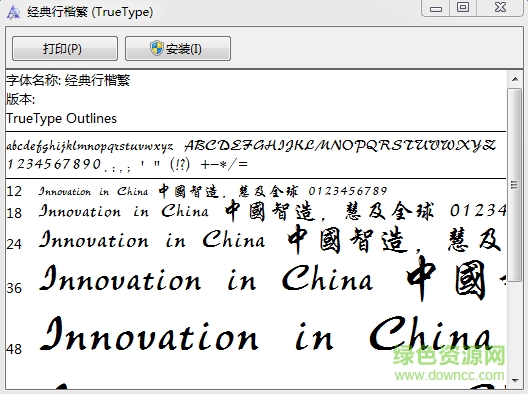
軟件介紹 軟件標簽: 經典字體 字體 經典行楷繁字體是經典字庫里的一款繁體字體,這款字體寫出來的字是俊秀美觀的,有著它獨特的特色與魅力,也是很多人都喜歡的一款字體,大家如果有需要的話可以來綠色資源網下載。安裝說明:方法一:控制面板/字體/文件/安裝新字體;方法二:直接將字體復制到C:\WINDOWS\Fonts。方法三:針對win7系統(tǒng),用戶只需選中字體右鍵安裝即可。注意事項本站所有字體資源僅供個人學習與參考,如需商業(yè)使用請到相關官網授權。 軟件截圖 上一張下一張(1 / 1) 安裝詳細截圖 猜你喜歡 行楷字體 經典字體 行楷字體 行楷字體大全是綠色資源網小編為大家打包整理的行楷字體ttf合集,包含了幾十款應用極廣的行楷體,適用于影視、廣告、平面、印刷各種行業(yè)領域,選擇多樣,下載便捷! 查看更多>> 漢儀蘇澤立行楷精修版簡 3.01M/中文/4.0/免費版下載 漢儀許靜行楷字體 2.44M/中文/4.4/下載 繁體行楷字體大全 46.87M/中文/2.5/下載 經典行楷簡體 常規(guī) 5.54M/中文/2.3/下載 文星簡行楷 3.41M/中文/6.6/下載 stxingkai 3.41M/中文/6.3/免費版下載 經典字體 綠色資源網小編為大家收集了經典字體的各種書體,比如經典綜藝體簡體,這種經典字體的整個字體效果還具有卡通元素;經典黑體簡是一款典型的簡體字體,是現(xiàn)代中文的一種標準化寫法,與繁體中文(又稱正體中文)相對等等,還有經典細宋簡、經典毛筆字體、經典繁淡古...,這一類字體在廣告設計、平面設計、學習等都有廣泛的應用,一次性給大家收集了,這樣大家用起來就方便多了。 查看更多>> 經典篆刻字體 2.14M/中文/5.0/下載 經典繁超黑 regular 1.17M/中文/5.0/下載 經典簡圓藝 2.44M/中文/5.0/下載 經典簡超宋 1.81M/中文/6.6/下載 經典簡方新 1.17M/中文/5.0/下載 簡圓新字體 1.95M/中文/5.0/下載 其他版本下載 標題 大小 更新日期 下載 下載地址 電腦版 經典行楷繁 點擊報錯 軟件無法下載或下載后無法使用,請點擊報錯,謝謝! 關閉報錯反饋 請描述您所遇到的錯誤,我們將盡快予以修正,謝謝! *必填項,請輸入內容 本類最新 經典繁方新 緇忓吀緇嗗渾綆 regutar 94款經典字體打包 免費版 經典行書簡 經典圖案字字體 經典特宋簡體 相關文章 Photoshop字體安裝使用方法和技巧 如何解決“無法新增字體”問題 Win 7系統(tǒng)安裝字體方法 網頁字體大小設置方法 怎么改網頁字體大小 在Linux系統(tǒng)中安裝字體的幾種方法 windows7字體顯示問題:打開某些程序的時候顯示的是亂碼 用戶評論 熱門評論 最新評論 發(fā)表評論 查看所有評論(0) 昵稱: 請不要評論無意義或臟話,我們所有評論會有人工審核. 字數(shù): 0/500 (您的評論需要經過審核才能顯示)